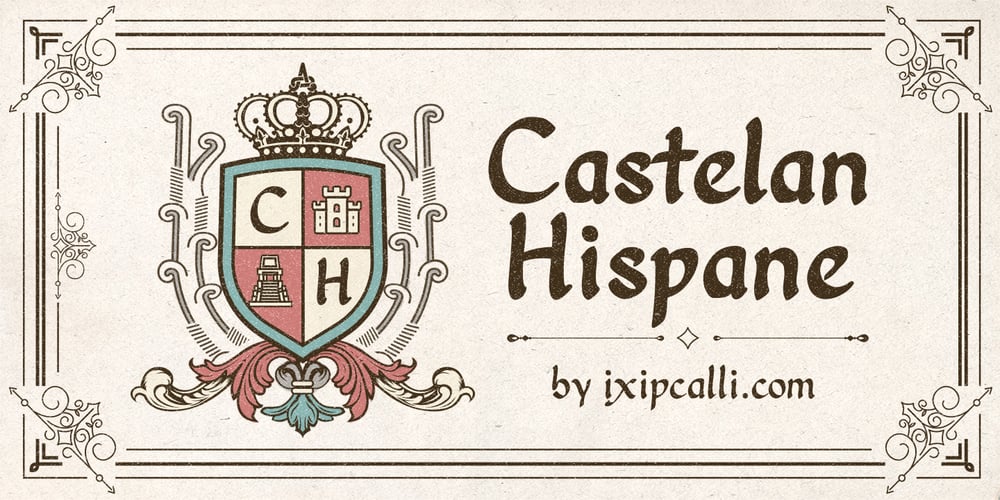
Castelan Hispane Font Family was designed by Francisco Arellano and published by Ixipcalli. Castelan Hispane contains 12 styles and family package options. La tipografía Castelan Hispane es una tipografía inspirada en documentos y textos antiguos históricos españoles del siglo XVI. Los trazos semi-medievales – cursivos, le dan una apariencia antigua pero también moderna para los proyectos en los que se desee utilizar la tipografía. Cuenta con seis estilos y tres pesos, ligera, regular y negrita. Cada peso contiene también su forma “itálica”.The Castelan Hispane typeface is a typeface inspired by ancient Spanish historical documents and texts from the 16th century. The semi-medieval – cursive strokes give it an ancient but also modern appearance for projects in which you want to use typography. It has six styles and three weights, light, regular and bold. Each weight also contains its “italic” form.